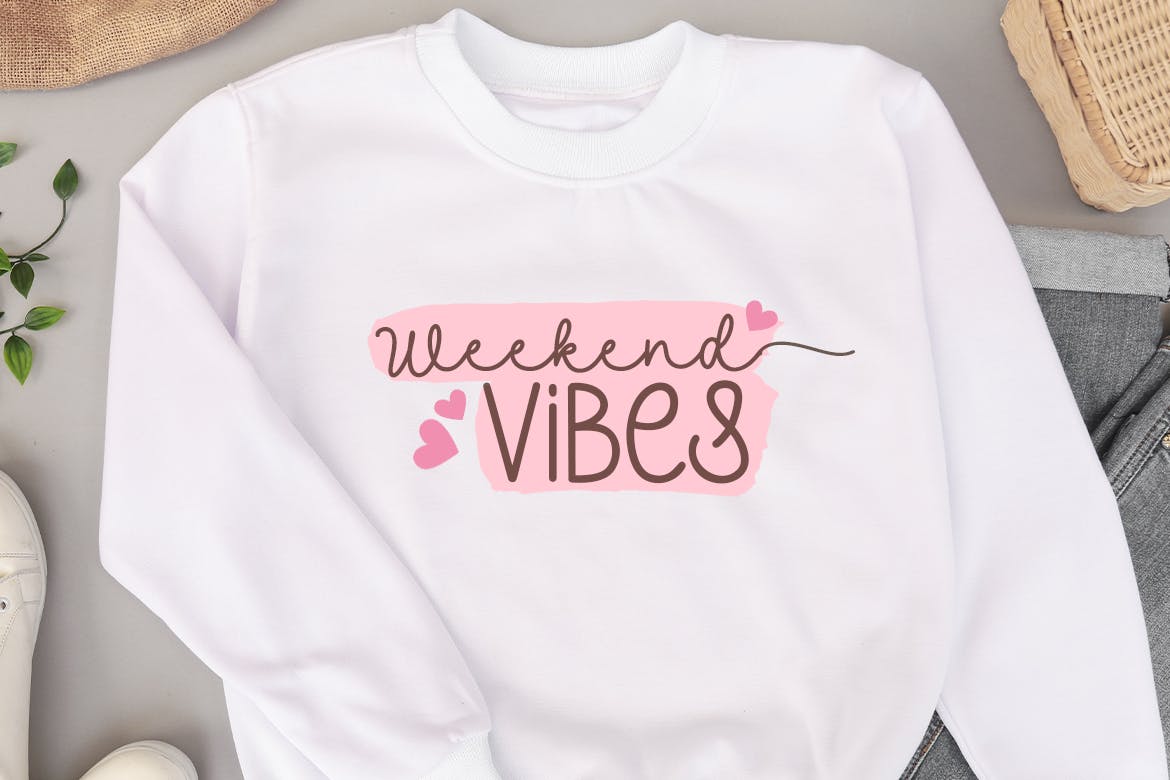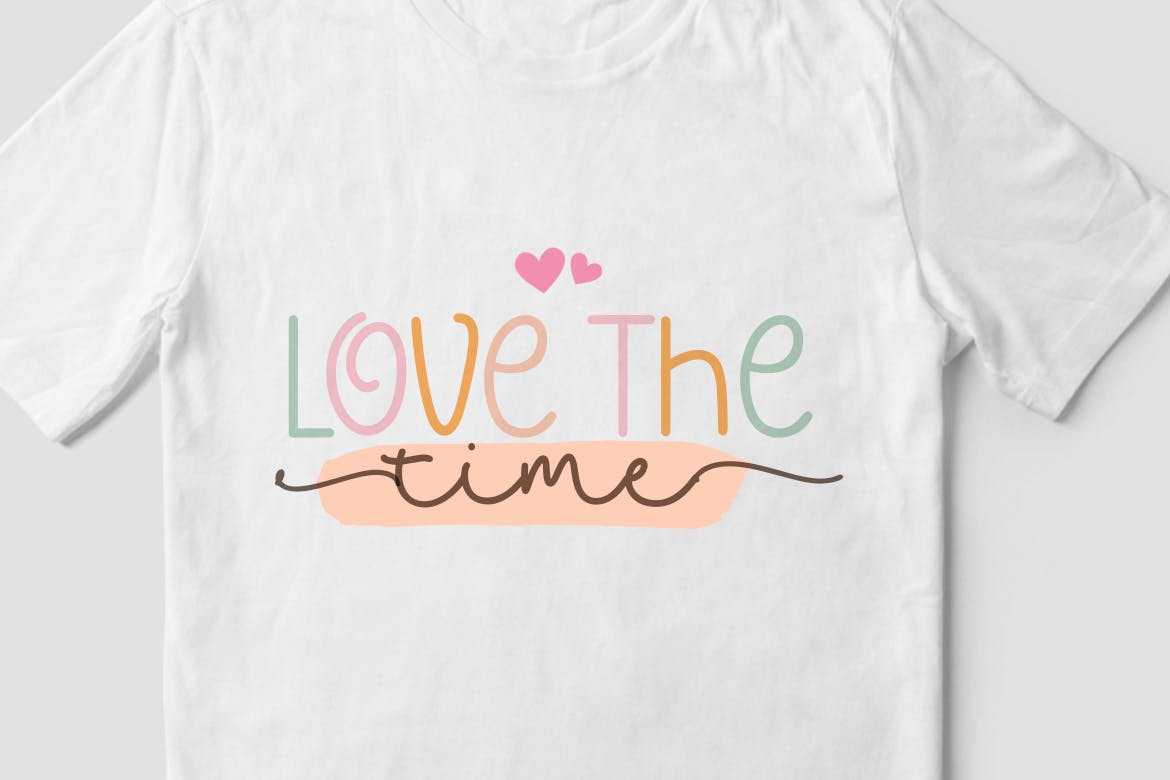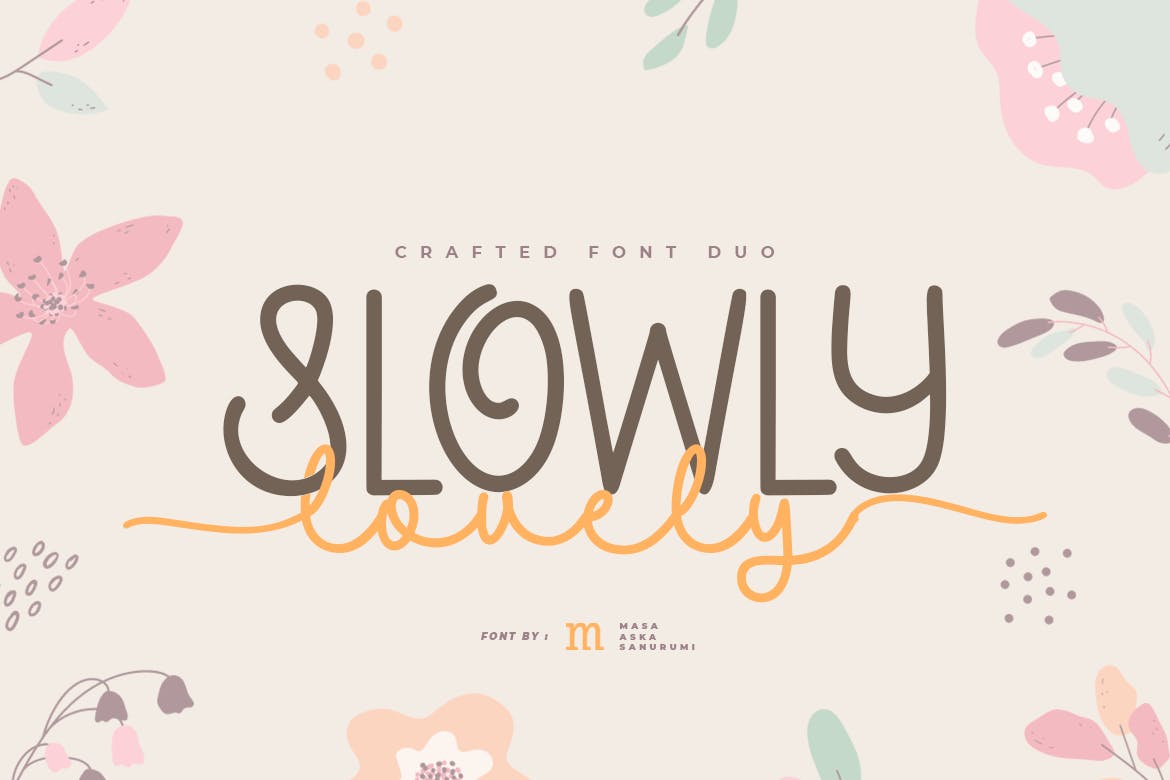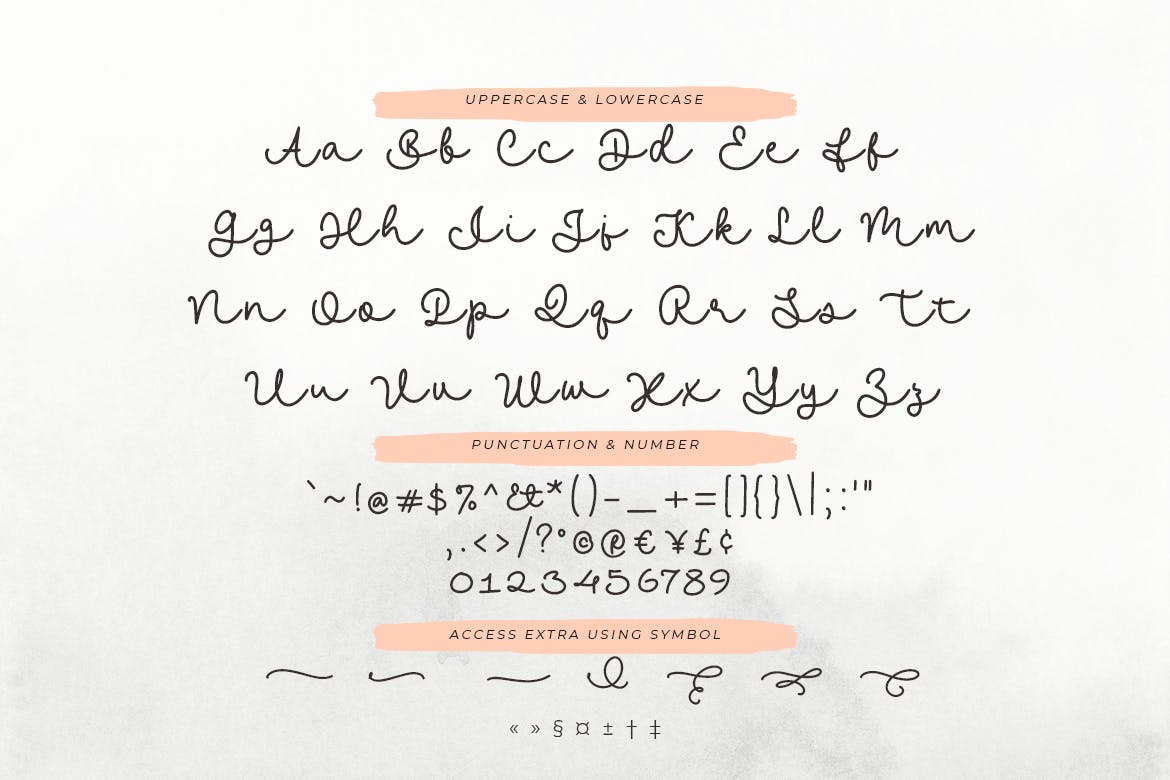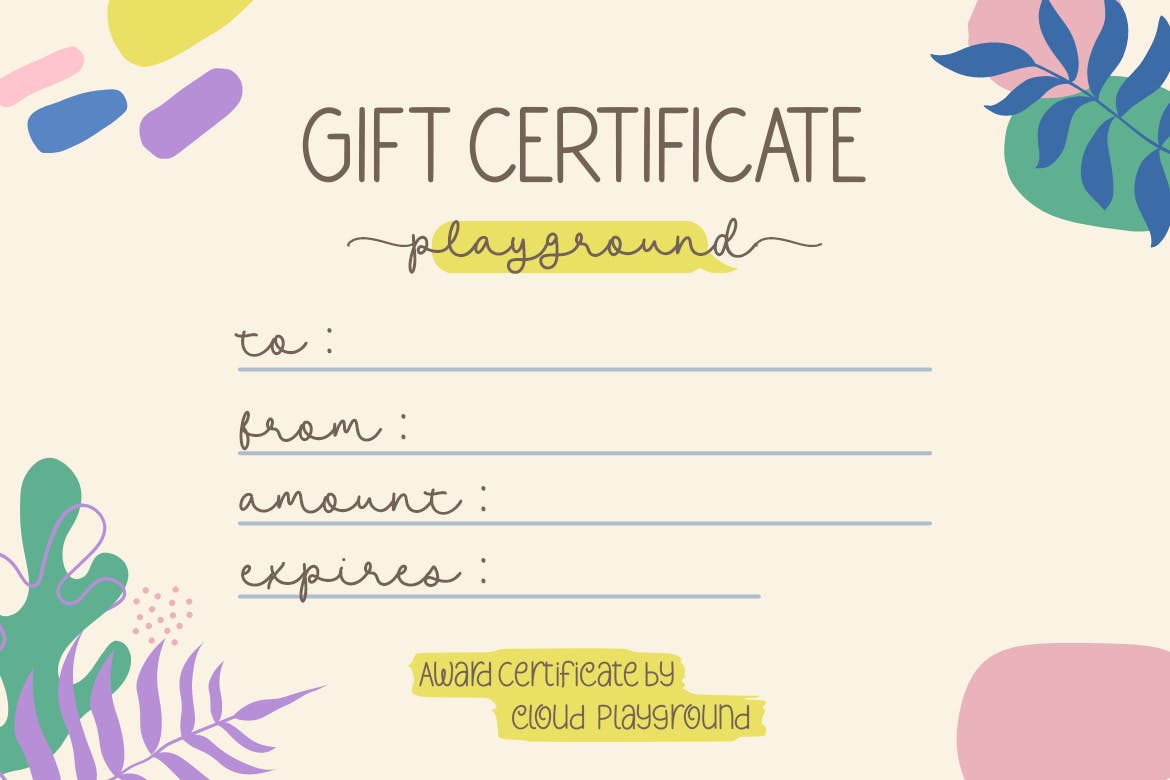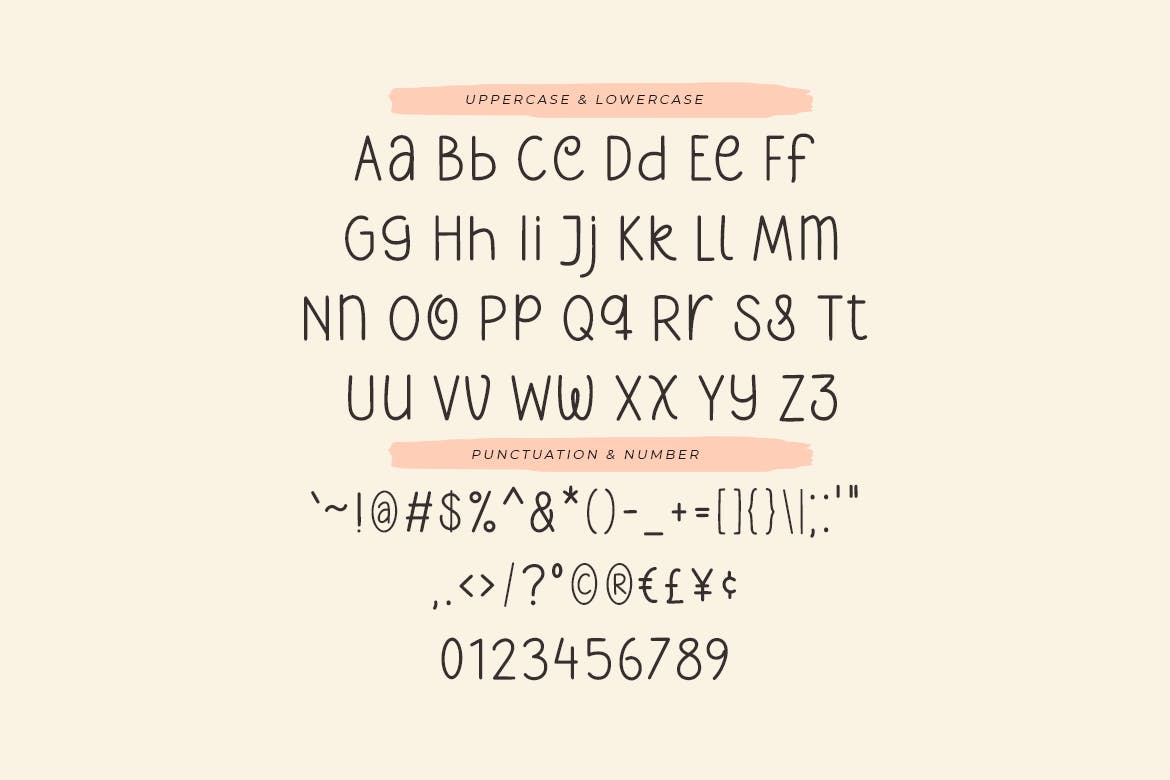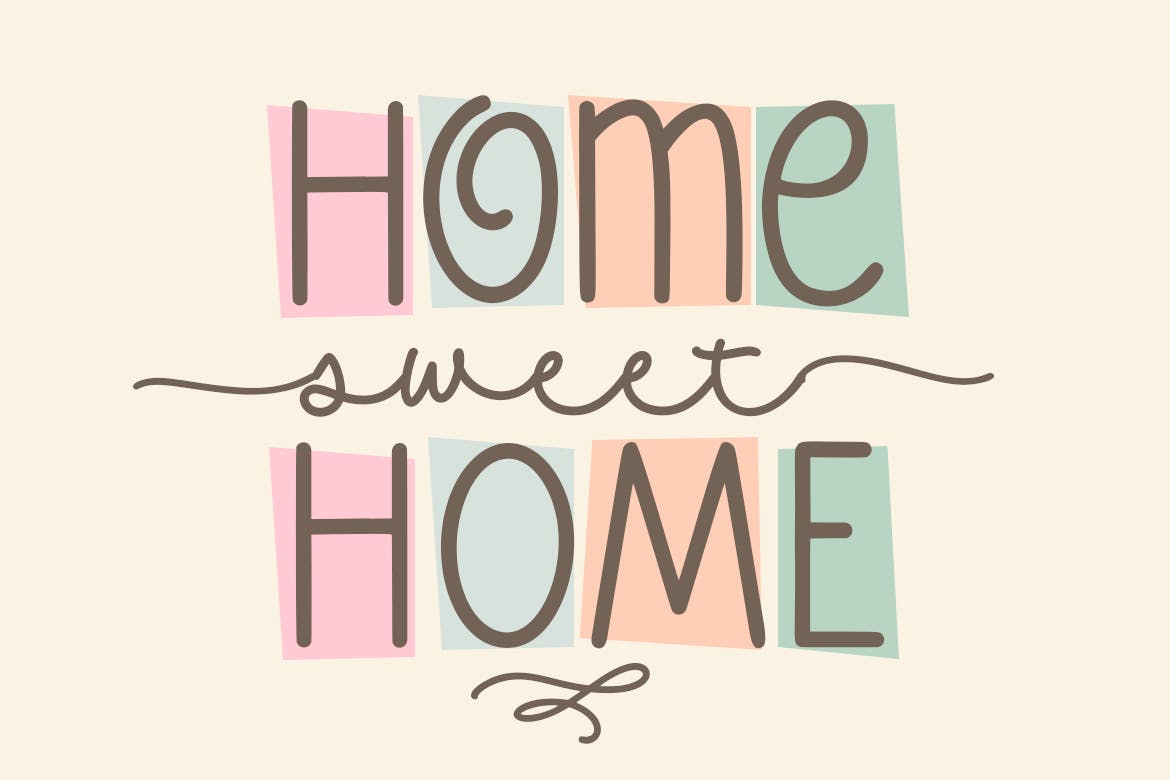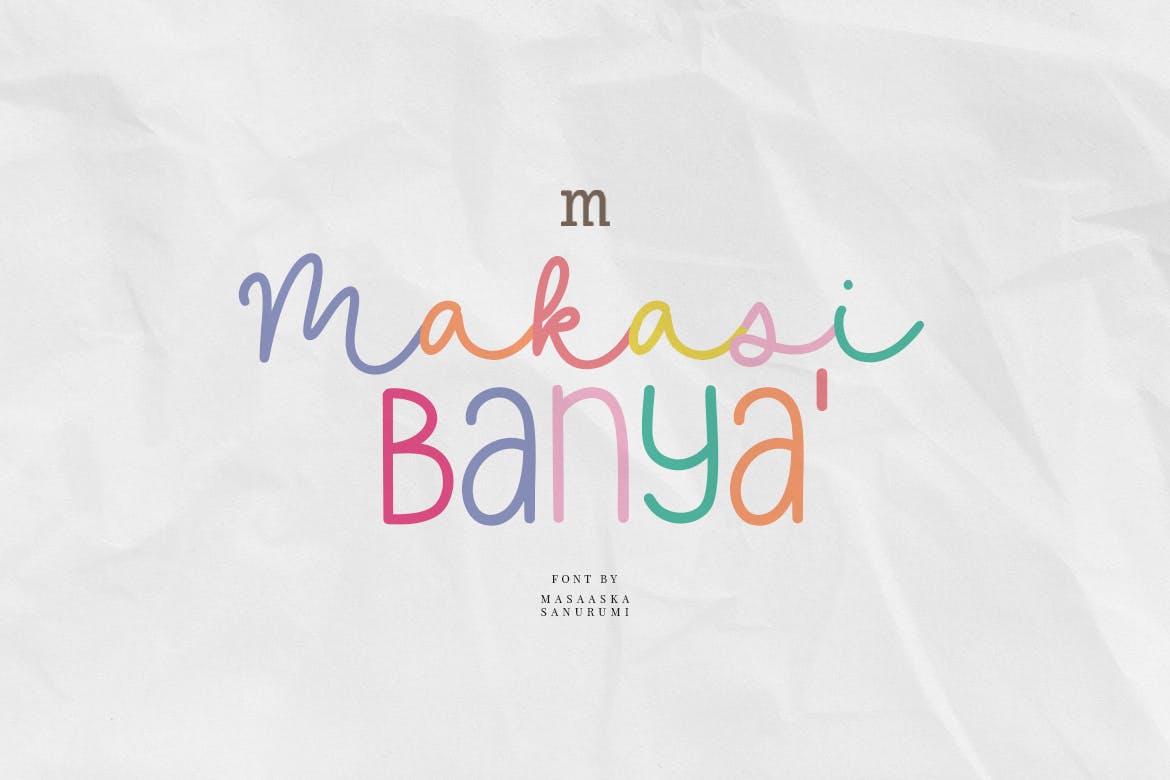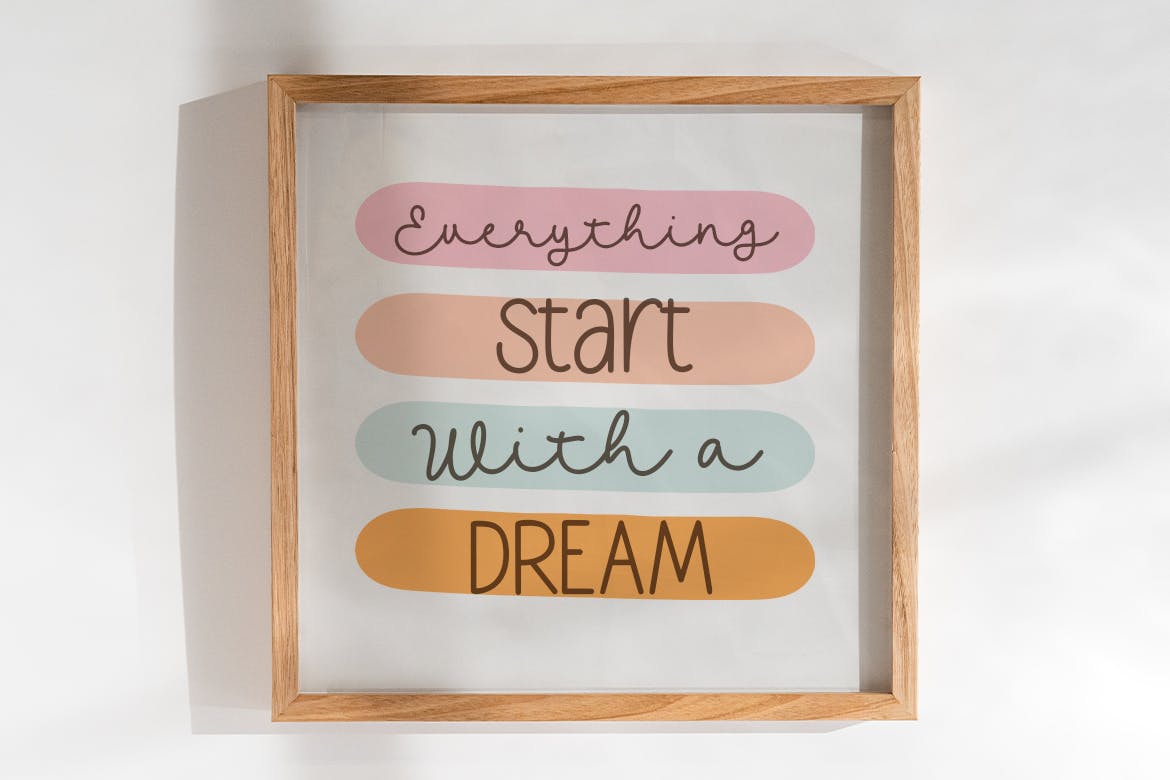
معرفی میکنیم، فونت Slowly Lovely Duo یک فونت دوگانه با طراحی خاص است که برای نیازهای پروژههای طراحی شما مناسب میباشد. این فونت برای تمهای عروسی، تولد، پستهای رسانههای اجتماعی، نقلقولها، لایهگذاری روی تصاویر، پوسترها، نیازهای چاپی، بنرهای وبسایت و موارد دیگر بسیار کاربردی است.